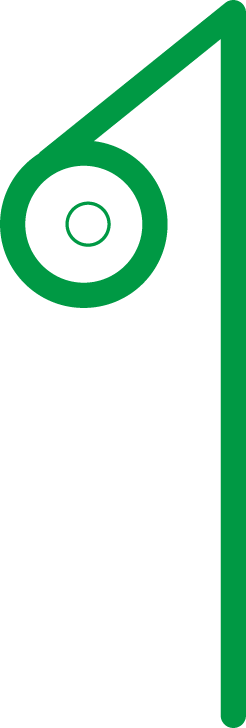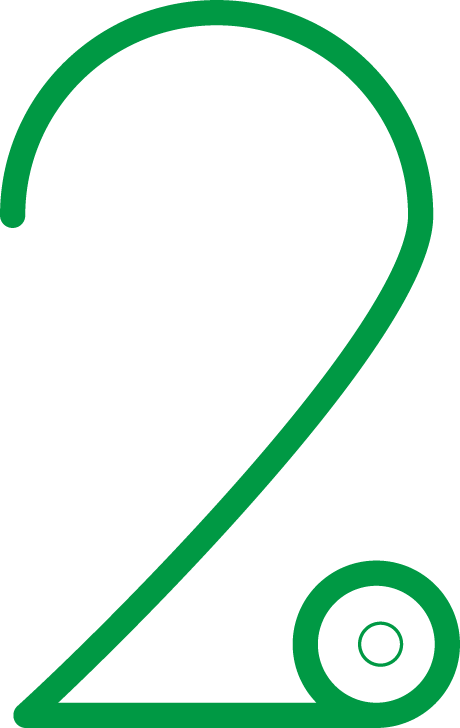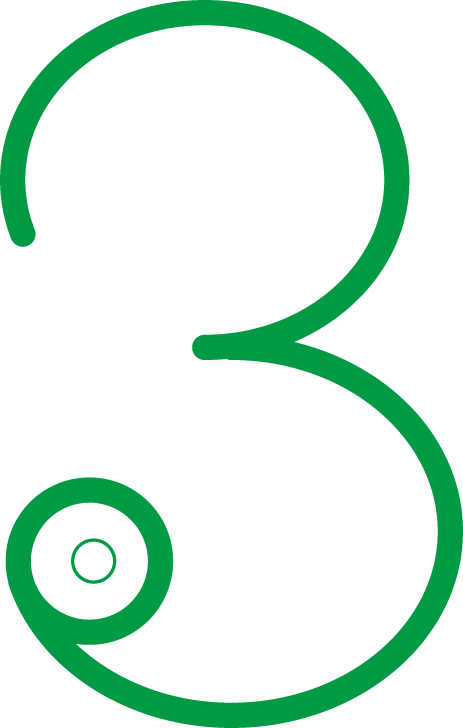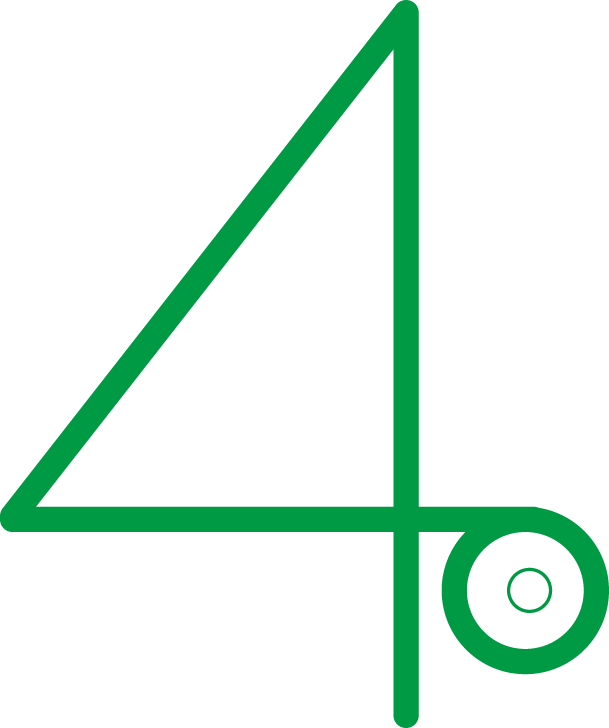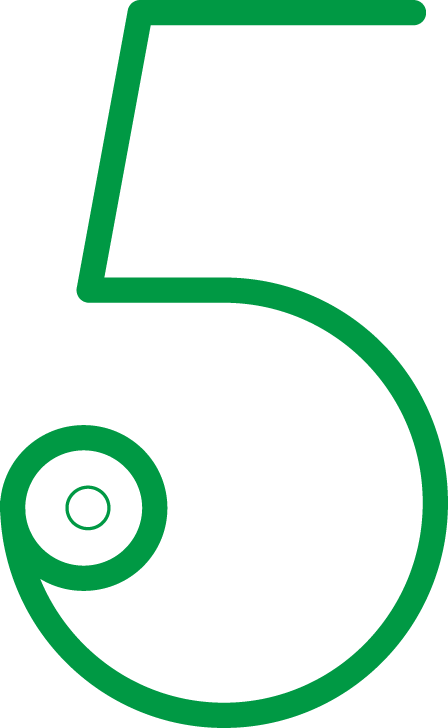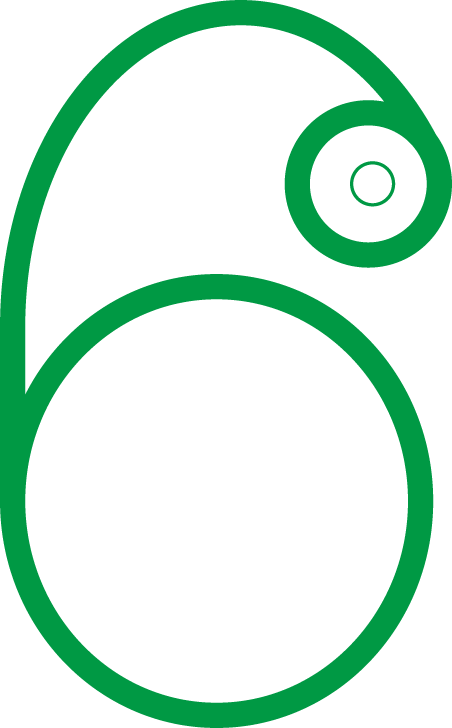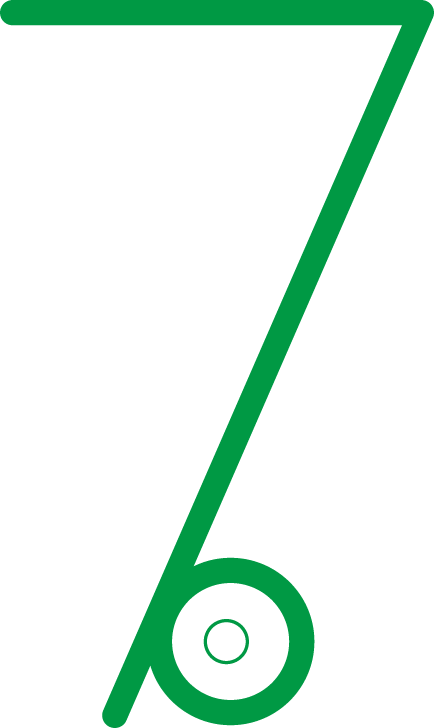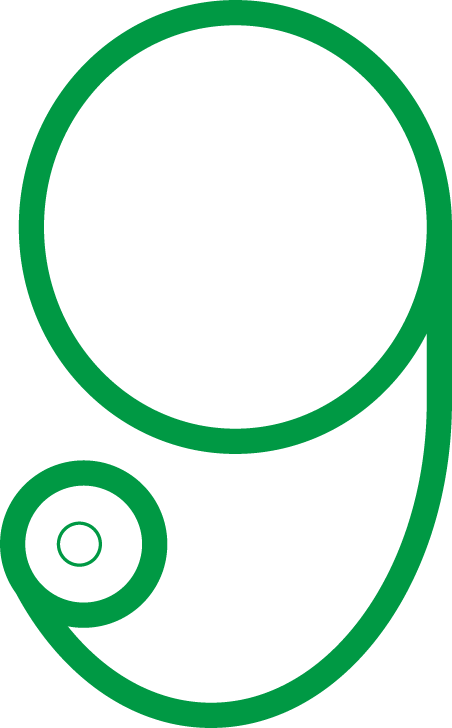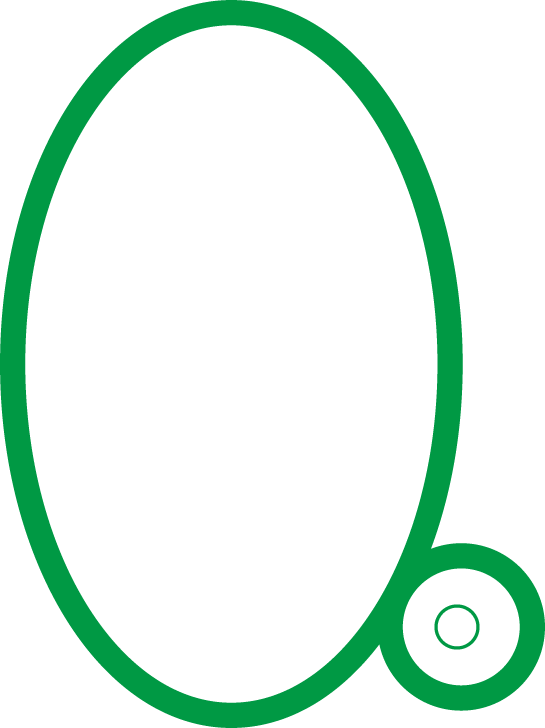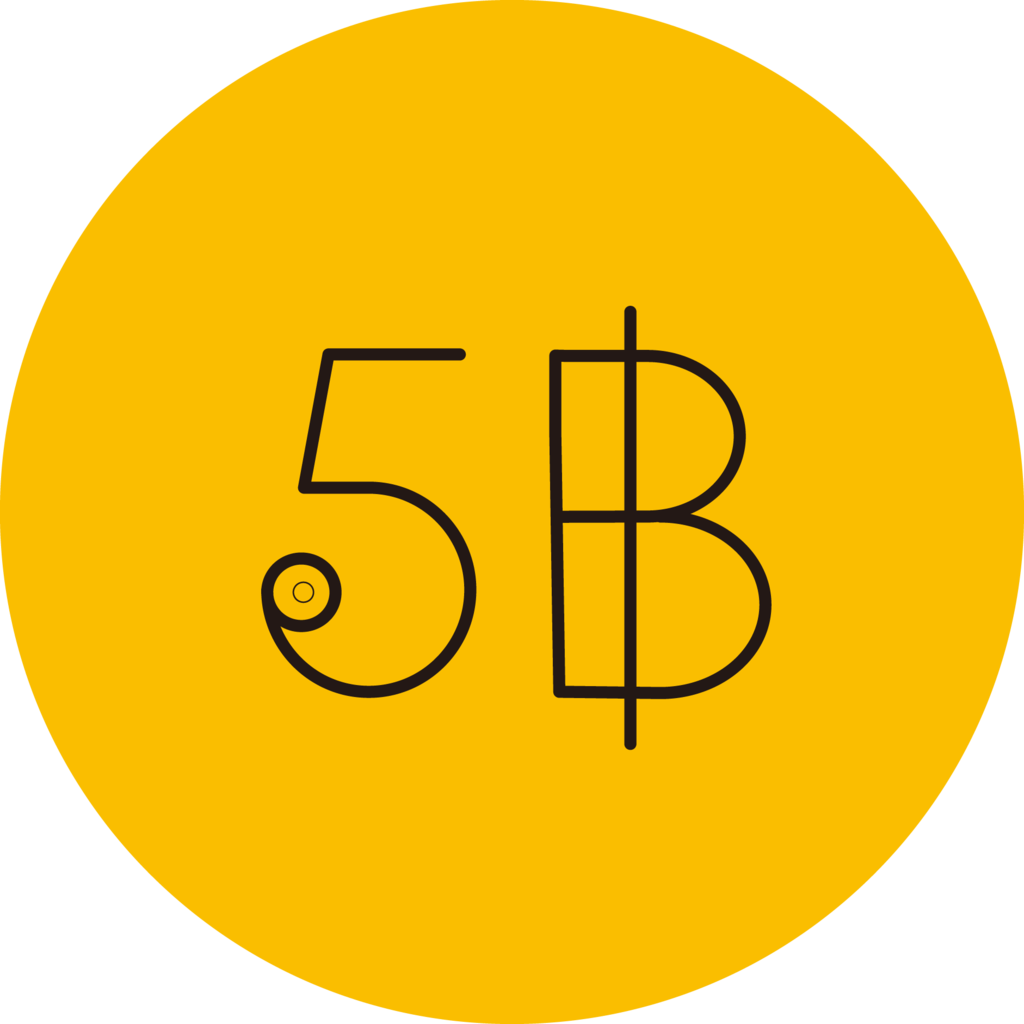
フォント「カメレオン」の数字
2017年3月11日のトムヤムクンという文字に続き、mojiru書体「カメレオン」の数字を作成した。
カメレオンの数字にも、他の文字と合わせてそれぞれ◎の装飾を加えた。
ちまにこの◎を私はカメレオンの目と呼んでいる。
まずは普通に数字を一文字ずつ作成したのち、後からカメレオンの目を加えている。
フォントサイズが小さいときに、眼球(◎の中の〇の部分)の部分がどうしても視認しにくいのが難点。
視認性を向上させるために◎の〇のストロークをもう少し太くするかどうか思案中。
実際にカメレオンの数字を使用した時、どんな感じになるのかイメージも作ってみた。
▼コイン風
バーツには◎の装飾を付けず、アルファベットのBの字形を作成してから線を引いた。
▼お札風
0が続くと少し五月蠅い気もする。
▼時計風
複数の目に囲まれている気がしないでもない。
目覚まし時計にしたら数字のカメレオンの視線が気になって起きれるか、そもそも眠れないか…、果たして。
数字の改善案も含めて時間がかかりそうだが、アルファベットも作成していきたい。